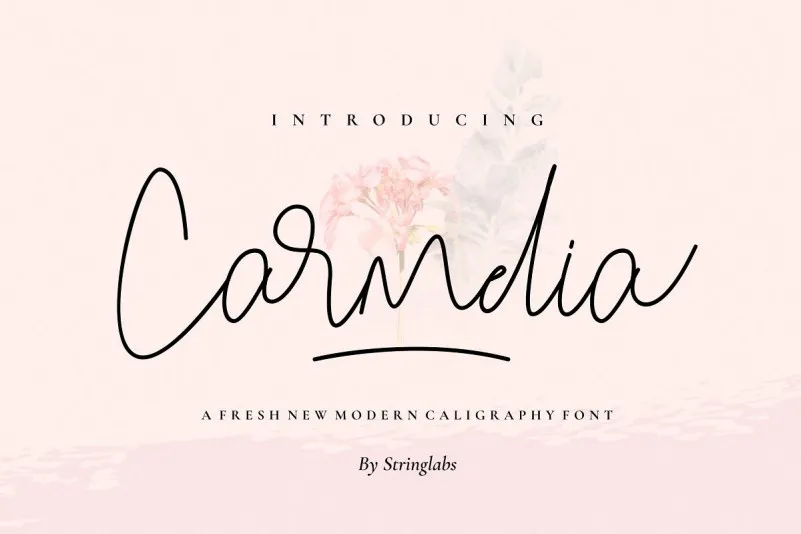
Carmelia Script Font – Fonte Grátis
Carmelia Script Font – Download Grátis
Carmelia Script Font
Introduzimos a Carmelia Font. Esta é uma fonte escrita à mão que se assemelha ao aspecto e sensação das notas escravizadas e desorganizadas. Foi especialmente criada para quem procura uma fonte de assinatura de escrita manual natural. A fonte foi desenvolvida pela nossa delicada artista do traçado. Ela foi projetada pelo StringLabs. Esta font pode ser usada em uma variedade de aplicações, como: fotografia, casamento, cerimônias, embalagens de produtos, tipo de logotipo, marcação, caligrafia, site/blog, cabeçalho da revista e também pode ser utilizada para fins comerciais.